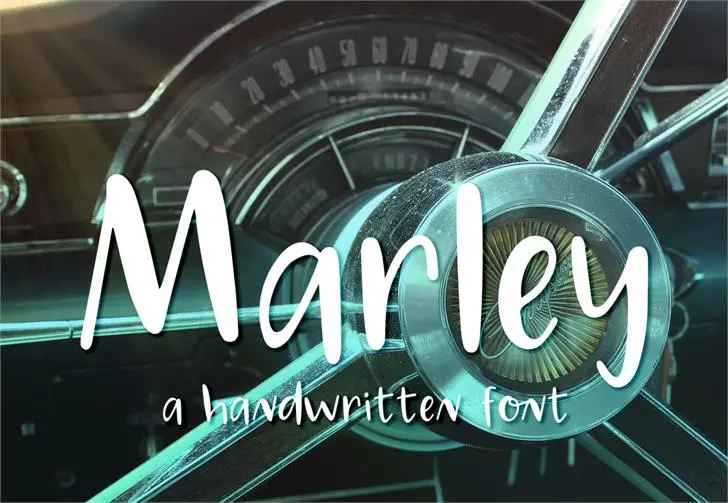
Aqui está uma descrição envolvente para a página de download da font ‘Marley Font’, mantendo-se fiel ao estilo informacional e convidativo do designer, sem inovar sobre as informações já fornecidas: Descubra Marley Font, uma elegante fonte brush que traz um toque autêntico à sua produção visual. Esta fonte é perfeita para designers gráficos que buscam uma sensação artística em seus projetos. Se você apreciou a Marley Font e considerou suas incríveis propriedades, por favor considere uma doação de $1. Isso ajudará a dedicar mais tempo ao design e criação de fontes como esta. Quem sabe, talvez o próximo projeto que criaremos juntos seja um verdadeiro sucesso. Marley Font é um excelente complemento para seu portfólio de recursos gráficos. Se você está procurando uma fonte brush com um toque especial, a Marley pode ser exatamente o que você precisa. Ela vai dar seu projeto aquele toque único e autêntico. Se você decidir fazer uma doação, garantimos que o seu investimento será bem-vindo para promover a criação de fontes como esta. Sempre com um objetivo claro em mente: criar recursos gráficos excepcionais para designers de todo o mundo. Por favor, use Marley Font com moderação apenas para fins pessoais. O arquivo .otf pode não ser compatível em todos os sistemas ou aplicações, então certifique-se de testá-lo antes do uso final. Se você tiver qualquer dúvida sobre a compatibilidade, estamos aqui para ajudar. Seja qual for o seu projeto, Marley Font está aqui para fornecer um design excepcionalmente elegante e único. Suas fontes Brush como nunca antes!